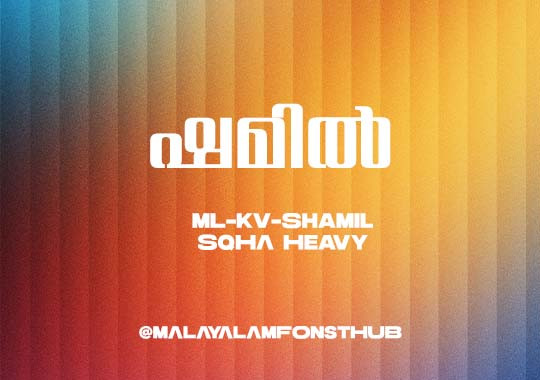
Shamil Heavy | Bold Malayalam Poster Font
തലക്കെട്ടുകൾക്കും പോസ്റ്റർ ഡിസൈനുകൾക്കും ഏറ്റവും അനുയോജ്യമായ ഒരു ഹെവി വെയിറ്റ് ഫോണ്ടാണ് ML-KV-Shamil-SqHA Heavy. ഇതിന്റെ കട്ടിയുള്ള അക്ഷരങ്ങൾ ഡിസൈനുകൾക്ക് കൂടുതൽ കരുത്തും ശ്രദ്ധയും നൽകുന്നു. സിനിമ പോസ്റ്ററുകൾക്കും സോഷ്യൽ മീഡിയ ഡിസൈനുകൾക്കും ഇത് മികച്ച ചോയ്സ് ആണ്.